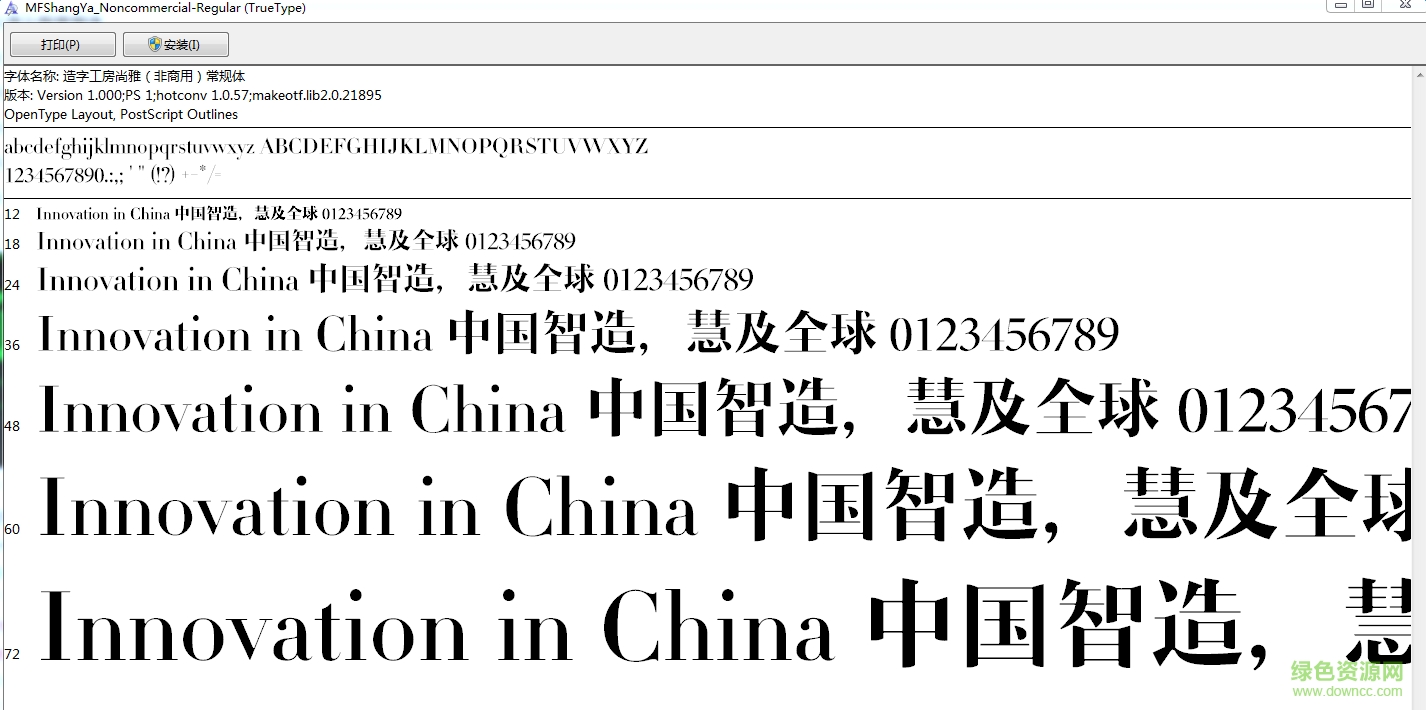
mfshangya_noncommercial regular
mfshangya regular字體又叫造字工房尚雅 非商用常規(guī)體,是一款襯線設(shè)計(jì)精致的中文宋體字體,筆形富于變化,清晰度高,適合用在文章排版設(shè)計(jì)中,有需要者歡迎免費(fèi)下載!
mfshangya字體特點(diǎn)
1.此款字體用途廣泛,主做標(biāo)題與副標(biāo)題之用;
2.筆畫設(shè)計(jì)簡潔、筆鋒柔和典雅,相比傳統(tǒng)宋體,更有多項(xiàng)個(gè)性化創(chuàng)新設(shè)計(jì)!
mfshangya regular
宋體發(fā)展介紹
「宋體」是一類字體的總稱,有很多字體都屬于這個(gè)范疇?,F(xiàn)代鉛字主要采用宋體印刷。后來依據(jù)西方文字的黑體和意大利體的方式,在漢字印刷體中也創(chuàng)造了黑體的鉛字。目前宋體、黑體、仿宋體和楷體成為漢字印刷的主要四種字體。